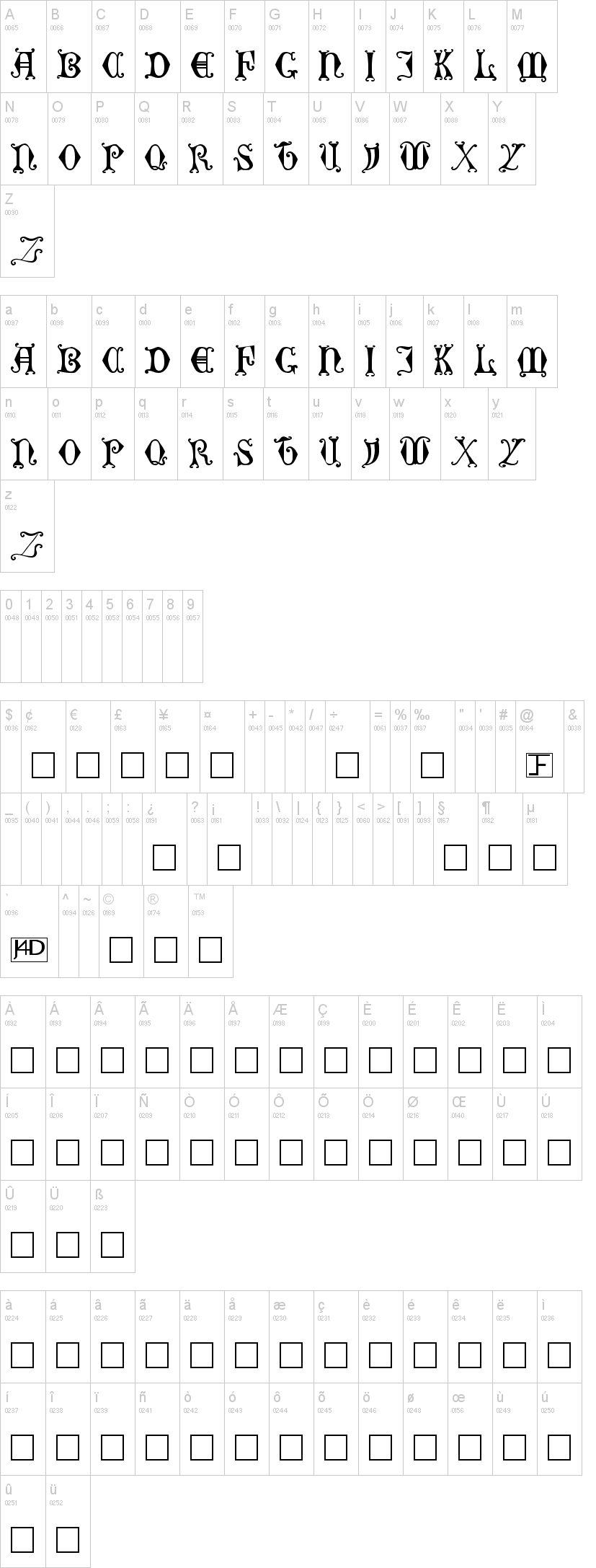
Curled Serif 字体是一种装饰性字体,它在常规 Serif 字体基础上增加了一些装饰性的卷曲和弯曲的线条。它的字母笔画有时候会有一些华丽和复杂的装饰,通常用于设计带有一定艺术性质的文本,如海报、宣传册等。 Curled Serif 字体的特点是在笔画和字形上都带有一些卷曲的装饰,这些装饰线条可以是花纹、卷曲或其他复杂的形状。这种字体通常比较华丽,适合用于标题、标志、海报、宣传册等需要引人注目的设计场合。 Curled Serif 字体的使用需要根据具体情况进行考虑,因为它的装饰性质可能会使得一些长文本不易阅读。一般来说,它适合用于短小的标题、标语、广告等设计需要。内容介绍
Curled Serif是一款非常不错的手写艺术字体,具有很好的视觉感,适合于文化类的宣传设计、商业类品牌的广告和产品包装设计以及个性化文字排版等较多场景。